何谓霸气?所谓霸气通俗来讲就是,一种力量感、征服感的体现,气势十足,无论是从哪个方面都散发出凌人的光芒,一种无人能及的境界。
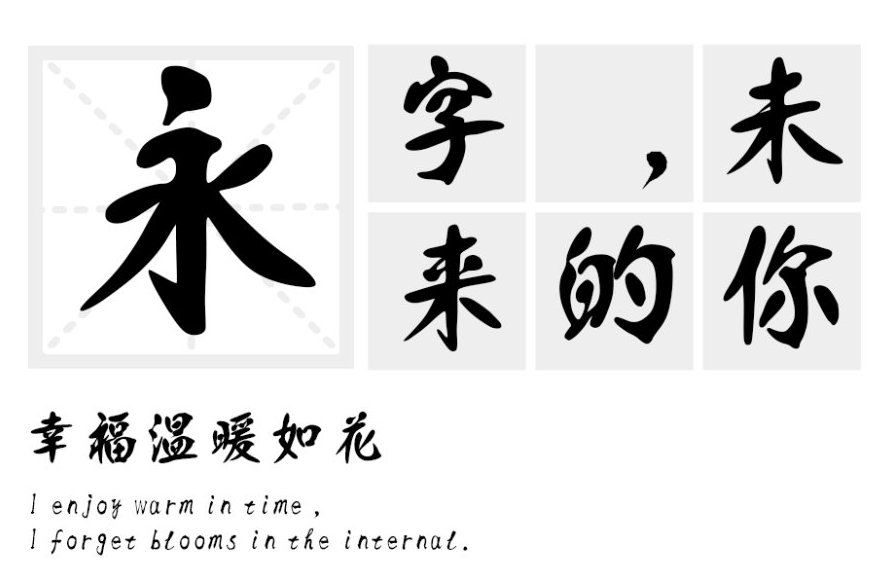
大家看看这张 图片字体 人一种 大气磅礴、浑然天成的感觉! 这款“汉标精工粗犷体”和它的名字一样,精致细腻中带着些许不拘小节的大气感,设计师是不是给在进行创作时的理念就是把表达对象有特征的感觉变得抽象化,转化为纯粹理性的美感的呈现。这款字体用在logo设计、书籍题目,包装设计,招牌设计等非常合适,令人耳目一新。
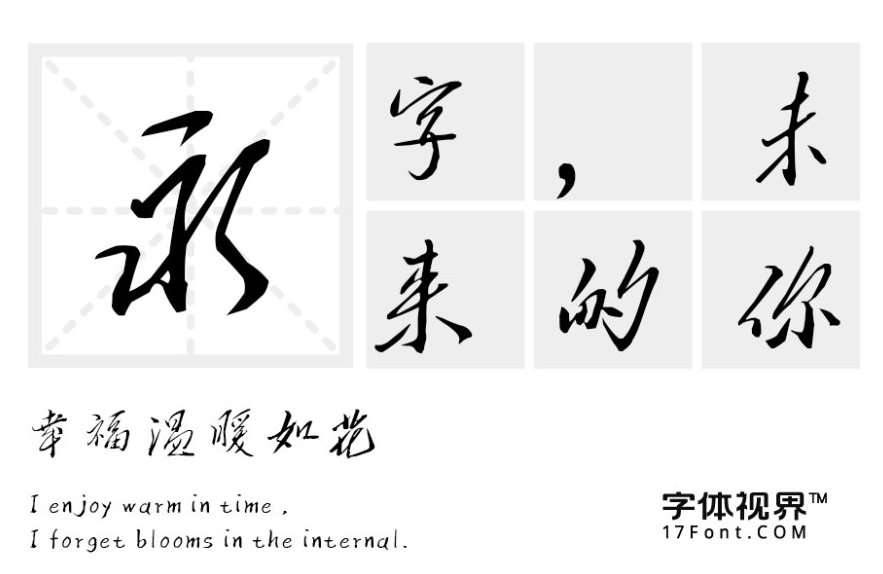
这款 “三极黄艺明手书”的字体风格,这款字体的笔法劲健却不失飘逸,灵动却不失雄浑之气,字形稚拙率意。我不由的想起了一首辉鸿豪气的诗《过零丁洋》中的“人让生自古谁无死,留取丹心照汗青。”这一句词,高风亮节的人生观,实为霸气的真意。